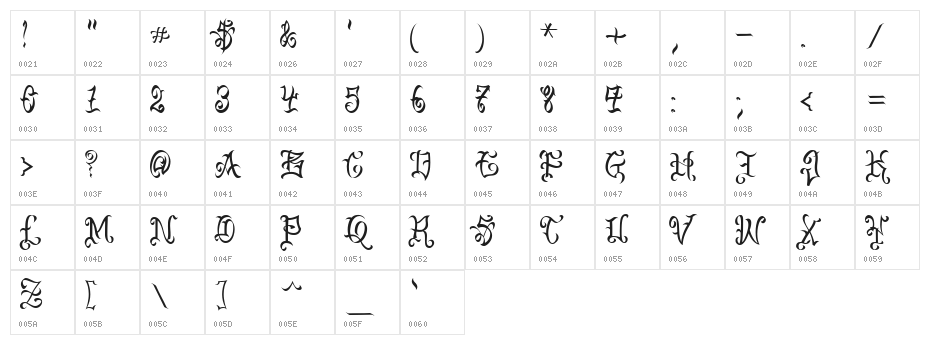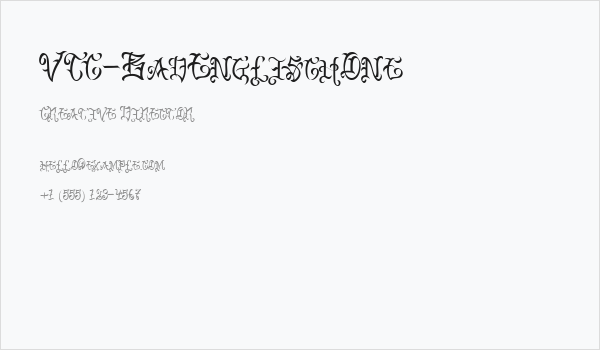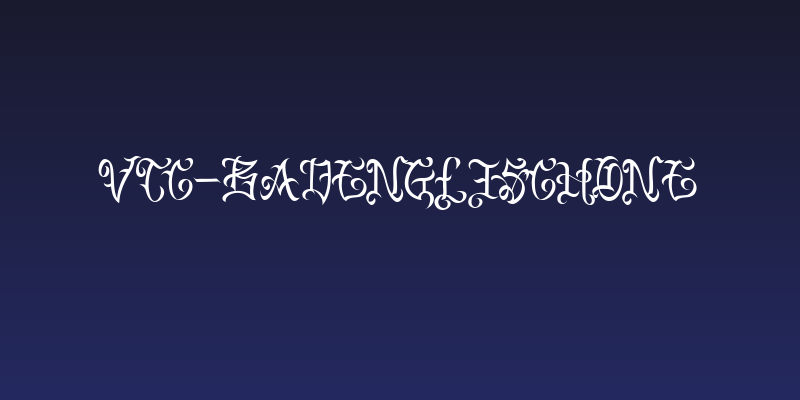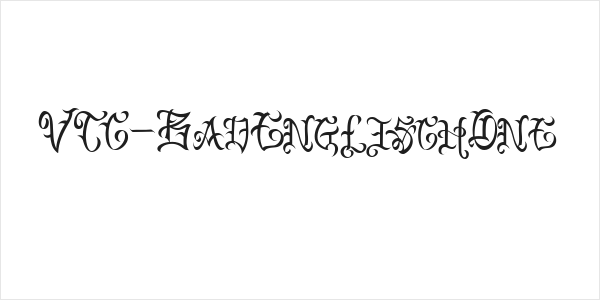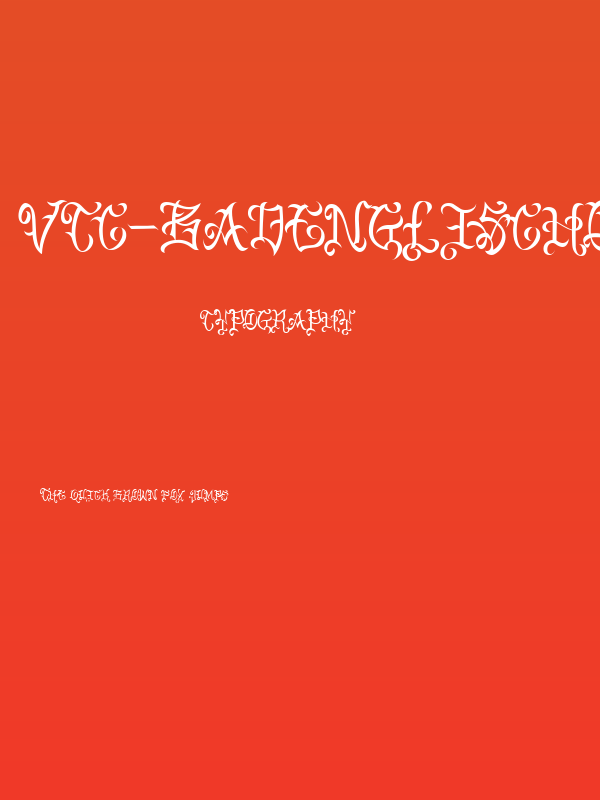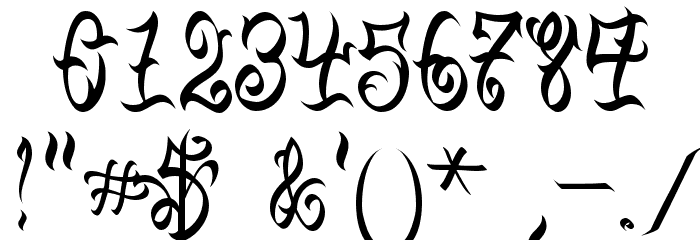
VTC-BadEnglischOne Font
| おすすめプロジェクト | Ideal for projects requiring a dramatic and historical touch, such as event invitations, book covers, posters, and branding for vintage-themed products. |